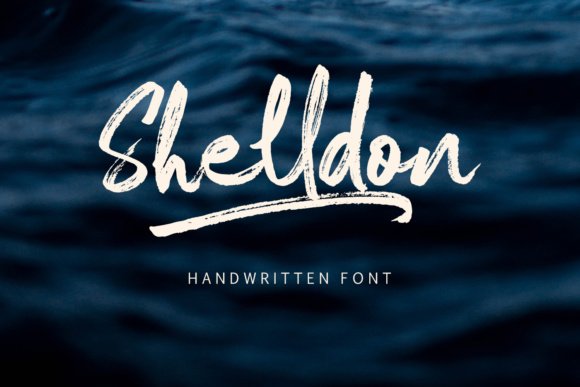
Shelldon - это рукописный шрифт в деревенском стиле.
Он обладает индивидуальным шармом, характеризуется быстрыми сухими штрихами и фирменным стилем.
В комплект Shelldon входят 3 различных шрифта:
- Shelldon: рукописный шрифт, содержащий прописные и строчные буквы, цифры и большое количество знаков препинания.
- Shelldon Alternate: Это вторая версия Shelldon с совершенно новым набором строчных и прописных символов. Если вы хотите, чтобы буквы не выглядели одинаково каждый раз, чтобы воссоздать индивидуальный стиль, или попробовать другую форму слова, просто переключитесь на этот шрифт, чтобы получить дополнительный вариант начертания.
- Shelldon Swash: Набор из 26 нарисованных вручную штрихов - идеальный завершающий штрих для подчеркивания вашего текста Northwell. Просто установите этот шрифт как отдельный, выберите его в меню шрифтов и введите любой символ A-Z для создания штриха.